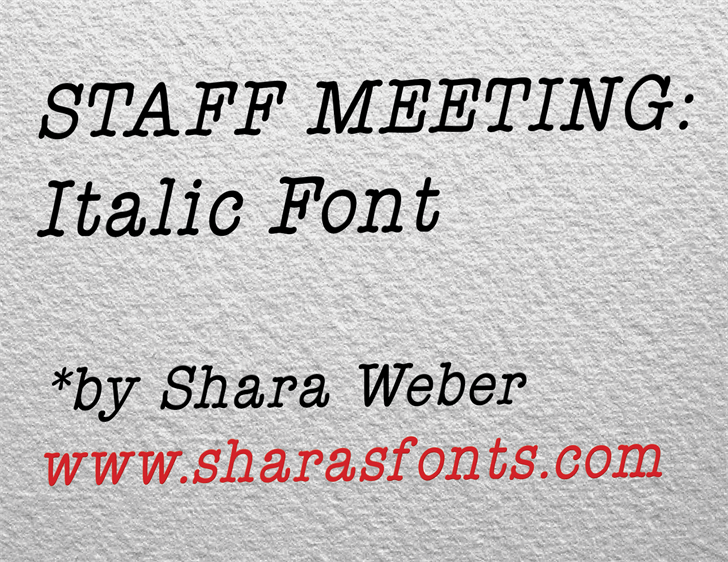
Staff Meeting Plain Italic Font – Download Grátis
A fonte “Staff Meeting Plain Italic Font” é uma seleção atraente para qualquer projeto que precise de um toque casual mas elegante. Desenvolvida pelo designer Hamilton, essa fonte pertence à categoria de Playful Fonts e se destaca por sua capacidade de adicionar um ar descontraído sem perder a seriedade necessária em reuniões de equipe. Com um design limpo e versátil, esta fonte oferece uma maneira divertida de personalizar textos importantes. É perfeita para criar contraste entre elementos formais do documento de reunião, como o título ou qualquer nota formal, com as informações mais flexíveis ou comentários pessoais dos membros da equipe. Seja para um email informal à sua equipe ou até mesmo para um documento de PowerPoint no ambiente de trabalho, “Staff Meeting Plain Italic Font” é uma escolha atraente que combina funcionalidade e estilo. Como adicional do designer Hamilton, essa fonte pode ser o ponto final perfeito para qualquer projeto em formato digital, especialmente aqueles que valorizam uma maneira leve mas atenciosa de tratar questões importantes.